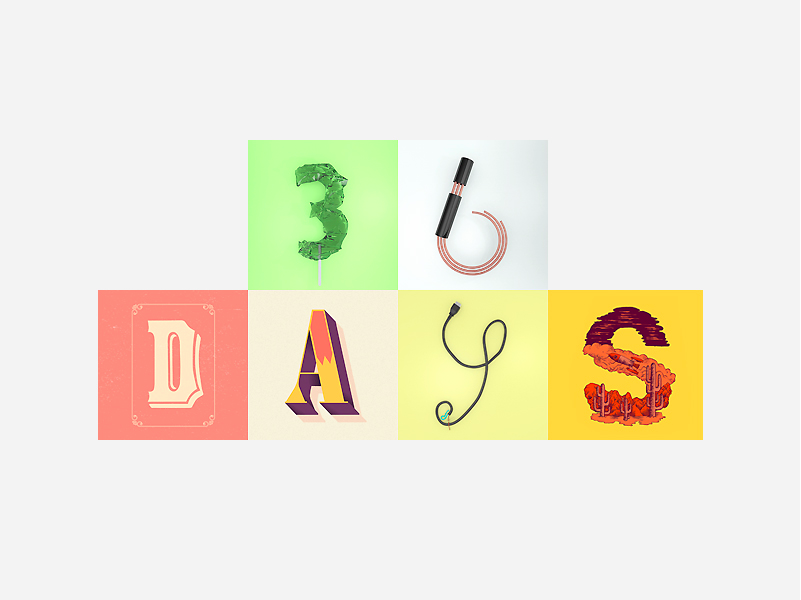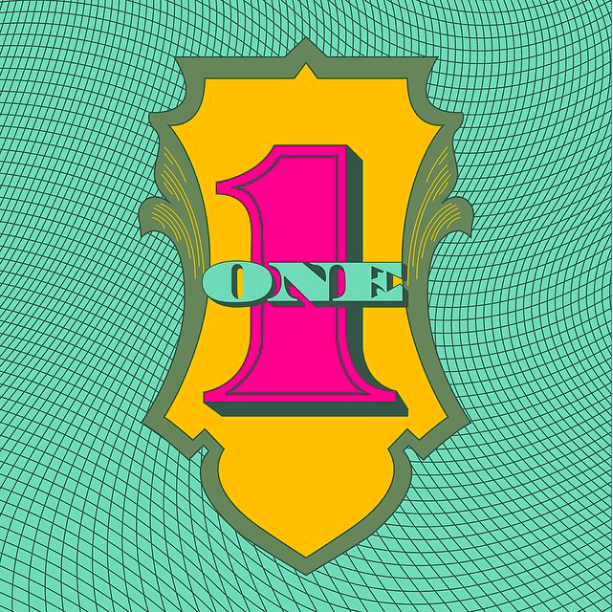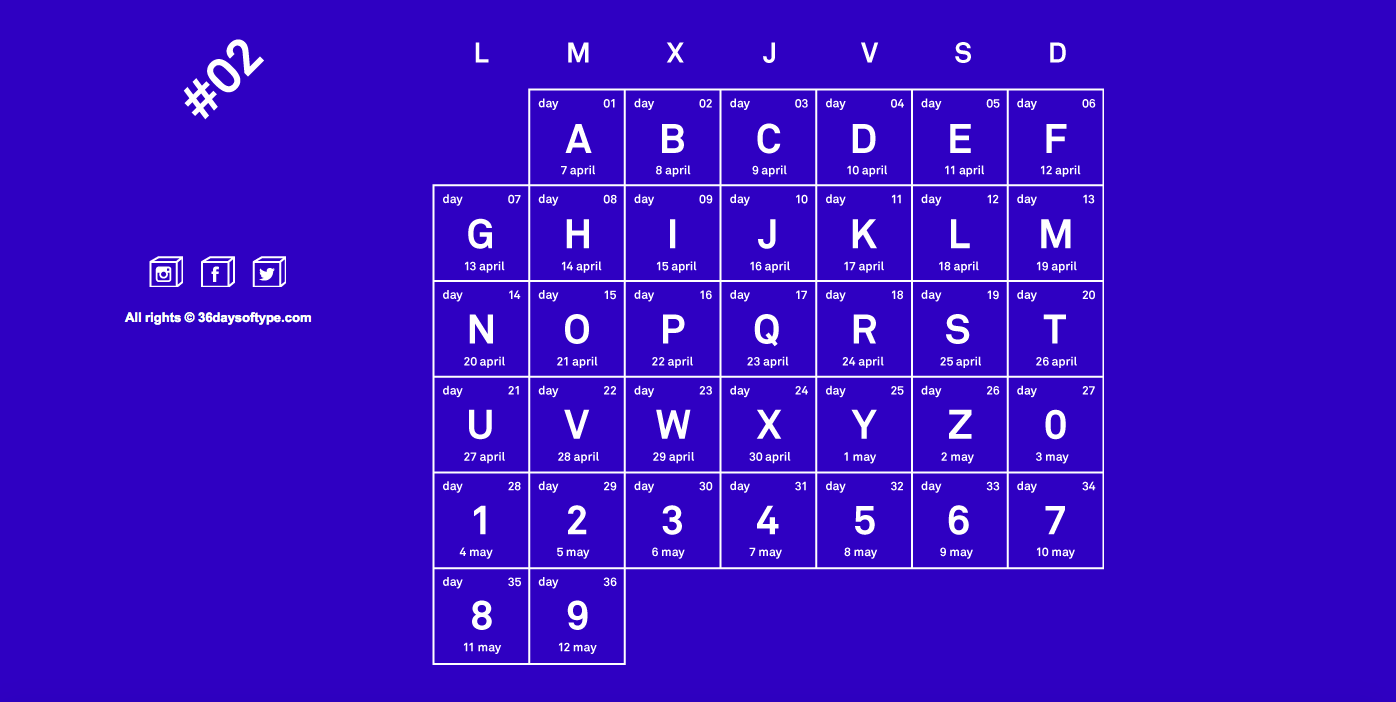
#36daysoftype – amantes de la tipografía, ¡es vuestro momento!
Queremos hablaros sobre la iniciativa creativa #36daysoftype, en la que cualquier diseñador puede aportar su visión y colaborar. Os lo explicamos brevemente en palabras de los fundadores del proyecto:
36 Days of Type es un proyecto que invita a diseñadores, ilustradores y artistas gráficos a que aporten su visión de los signos que forman nuestro alfabeto.
Durante 36 días de creatividad sin descanso, se reta a los participantes a diseñar una letra o número cada día hasta generar un alfabeto completo, dando lugar a una imagen global sobre la capacidad de representar un mismo signo desde muchas perspectivas diferentes.
El proyecto se desarrolla íntegramente en Instagram y lo mejor de todo es que hay libertad total a la hora de diseñar. Echa un vistazo para ver todas las propuestas que ya se han ido colocando y súbete al carro con las tuyas propias.
El primer lunes de mayo se inaugura con la primera cifra, el número 1, y para abrir la veda han invitado al estudio Mucho para que aporte su visión.
Ojo al calendario y no te pierdas. Si quieres colaborar, tienes hasta el 12 de mayo para sumarte a esta iniciativa.